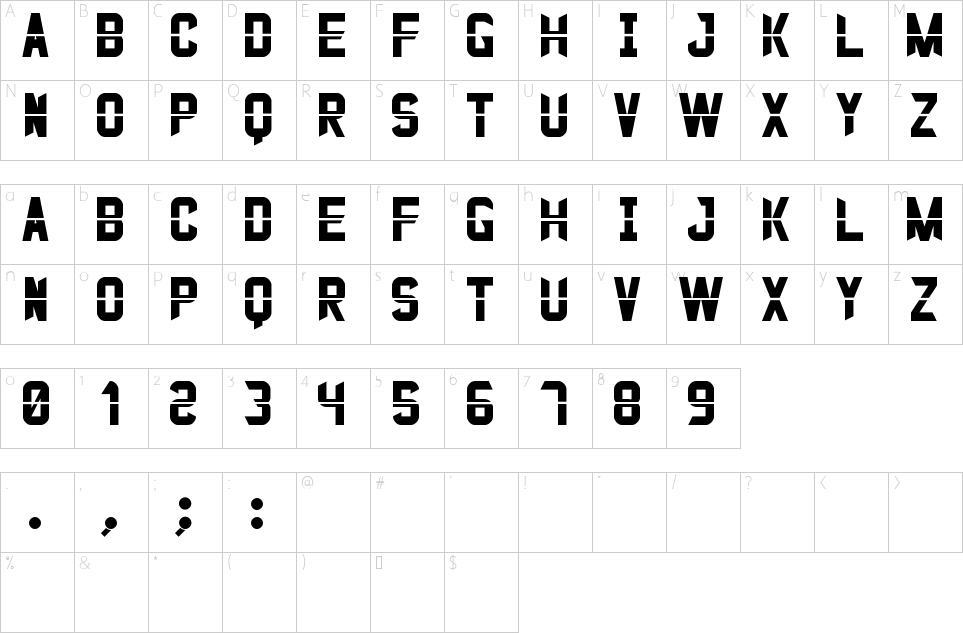
A fonte Justo St é uma escolha ótima para projetos de design gráfico que valorizam um estilo limpo e minimalista. Desenvolvida por um designer anônimo, a Justo St foi projetada para agregar um toque moderno e elegante a qualquer projeto. Esta fonte foi especialmente popular entre os designers brasileiros, com downloads registrados em mais de 49.900 vezes. Com seu design clean e minimalista, a Justo St é perfeita para criar rótulos de embalagens, headlines para sites, e qualquer tipo de identidade visual que você possa imaginar. Se você busca uma fonte de graça que se adapta bem à variedade de projetos de design, a Justo St é uma excelente escolha para se juntar à sua coleção de fontes.